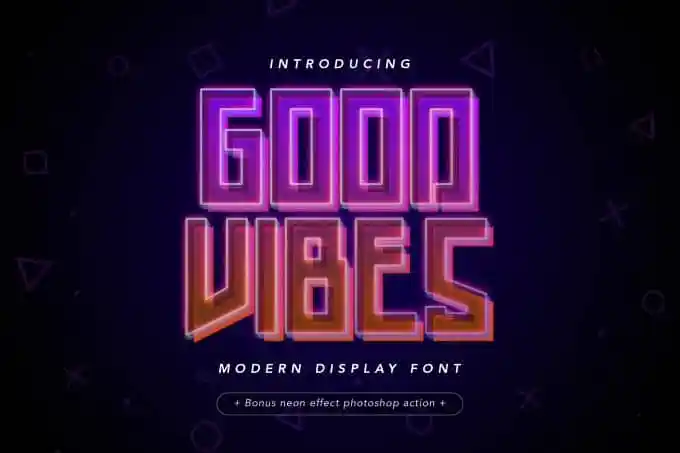
Good Vibes Display Font – Download Grátis
A Good Vibes Display Font é uma exuberante tipografia moderna e clássica, ideal para aplicações que buscam um equilíbrio entre elegância e modernidade. Desenvolvida por Peterdraw na 99designs, esta fonte apresenta características inspiradas em neon, tecnologia moderna e esportes, criando uma atmosfera vibrante e atemporal. Seus traços são fluidos e harmoniosos, perfeitamente adequados para logotipos, textos de citações ou sobre temas esportivos. Sua alta legibilidade a torna ideal para ambientes escuros, música ou qualquer imagem de fundo que mereça um overlay de texto elegante e sofisticado. Com seu design versátil, é perfeito para estilos contemporâneos e clássicos, oferecendo uma opção única para projetos digitais e impressos.